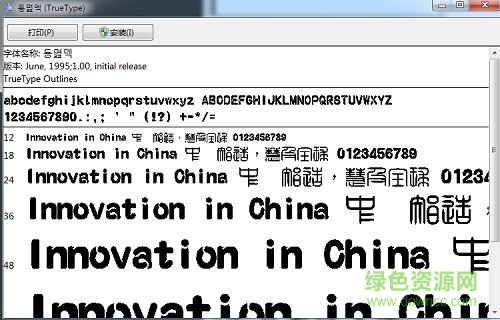
富漢通粗角篆是為喜歡各色藝術(shù)字體的朋友準(zhǔn)備的一款個(gè)性十足的中文字體,這款字體字庫(kù)完整,形體優(yōu)美,非常的具有觀賞性,有需要?dú)g迎免費(fèi)下載!
富漢通粗角篆是一款篆字字體,其特點(diǎn)是形體勻逼齊整、字體較籀文容易書寫。篆體在漢文字發(fā)展史上,它是大篆由隸、楷之間的過渡。